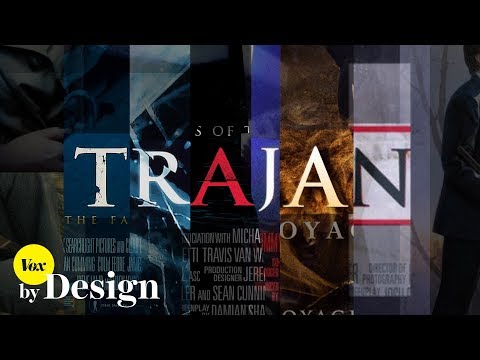
Deshalb ist die Schriftart Trajan auf etlichen Filmplakaten zu sehen hollywood-movie-posters-Trajan
Ähnliche Bildkompositionen oder Schriftarten auf Filmplakaten sind euch doch sicherlich auch schon einmal aufgefallen. Gerade bei typischen Vertretern von Genres werden gerne mal die gleichen Stilmittel genutzt, was ja auch irgendwie logisch ist, immerhin hat sich durch den jahrelangen Einsatz bestimmter Optiken beim Zuschauer festgesetzt, um was es sich handeln müsste, wenn man eben genau das zu sehen bekommt. Doch eine Schriftart übertreibt es total: Trajan.
Vox hat mit Designer Yves Peters darüber gesprochen, dass unnormal viele Filmplakate diese Schriftart einsetzen. Vermutlich achtet ihr nach Anblick des Videos automatisch in nächster Zeit darauf und werdet allerlei „Oha!“-Momente erleben.
„For the past 25 years, one typeface has dominated Hollywood typography: Trajan. It’s everywhere, from Shakespearean epic classics like Titus to gory modern flicks like The Human Centipede. It was even the official typeface of the Academy Awards for a while. In movie poster design, if you want to make a film look official, you use Trajan. So how did that happen? Designer Yves Peters set out to answer that question.“